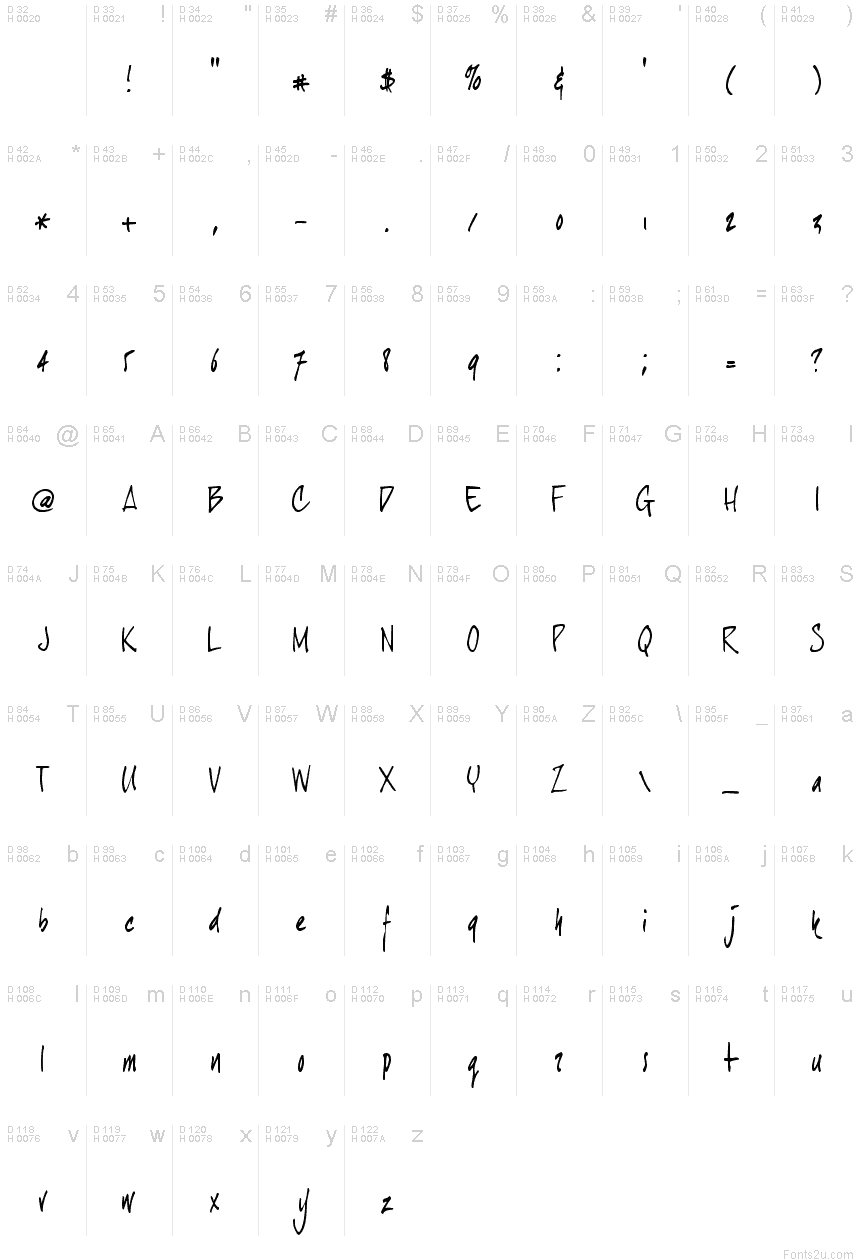
joeHand 字体
joeHand 字体家族,包含 4 款字体
joeHand
由 Joebob Graff-x 2000 设计的 joeHand 是一款免费手写字体,捕捉了记号笔在纸上快速书写时的那种墨迹感。高瘦的字形和略微不规则的节奏,让文字既显露个性又充满随性,同时字间距又保持得足够紧凑,确保短文本段落依然清晰易读。这种笔触就像是在速写本封面上随手签下的自信签名。
使用 joeHand 可以为名言短句、海报、产品标签、休闲 Logo、杂志及社交媒体视觉设计增添一份真诚与人性化气息。这款免费字体在大尺寸下表现尤为出色,让笔触自然呼吸,再搭配一款简洁的无衬线字体作为正文,能让手写风格保持清晰且极具表现力。